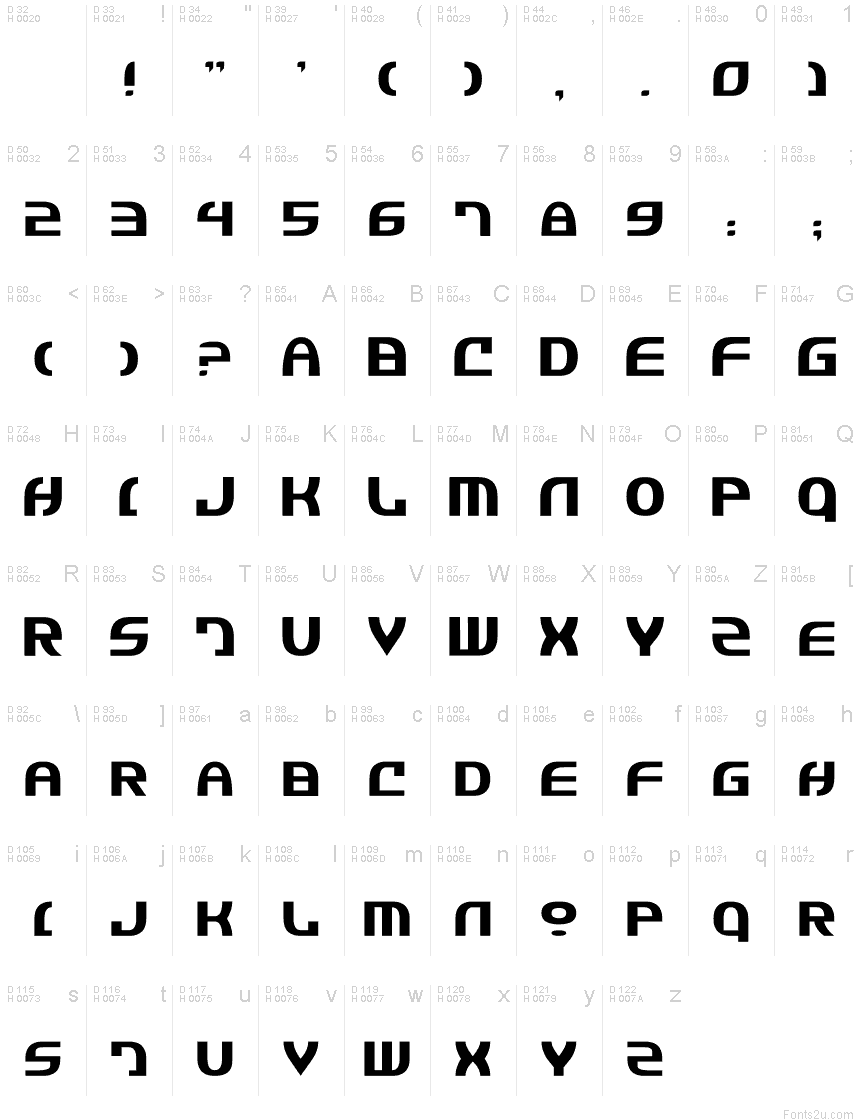
Jannisary Extra von Iconian Fonts ist eine kostenlose, futuristische Display-Schrift. Ihre wuchtigen, unten verankerten Buchstaben wirken wie massive schwarze Säulen, während die Oberseiten sauber abgeschnitten sind und einen eleganten, urbanen Skyline-Effekt erzeugen. Dank der abgerundeten Innenkurven wirkt das Schriftbild trotz des kräftigen, digitalen Designs nicht zu hart und bleibt auf einen Blick gut lesbar.
Mit Jannisary Extra fühlen sich Überschriften an, als würden sie über die Seite marschieren – stark, rhythmisch und kompromisslos Sci-Fi. Diese kostenlose Schrift glänzt bei Gaming-Titeln, Technik-Postern, Streaming-Overlays, Elektro-Albumcovern und futuristischem Produktdesign. Kombinieren Sie sie am besten mit einer schlichten geometrischen Sans-Serif für den Fließtext und lassen Sie Jannisary Extra bei großen, aufmerksamkeitsstarken Schlagzeilen glänzen.
Jannisary Extra